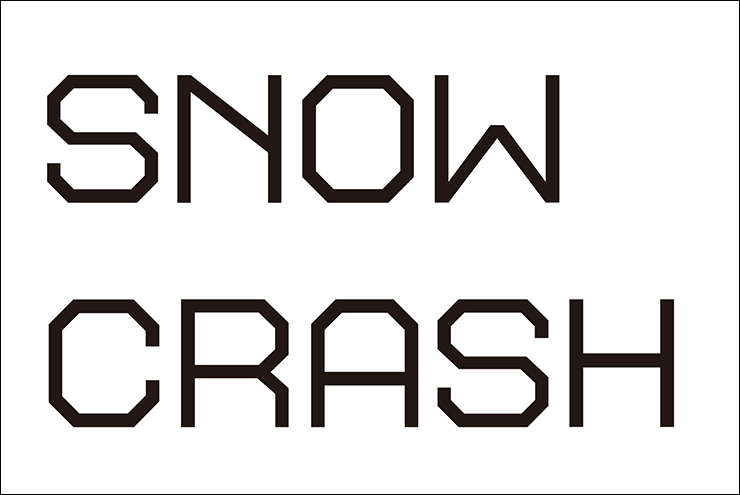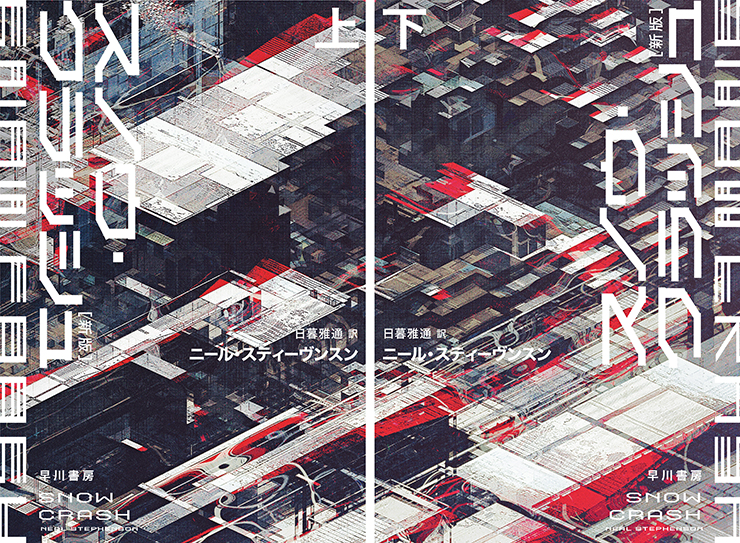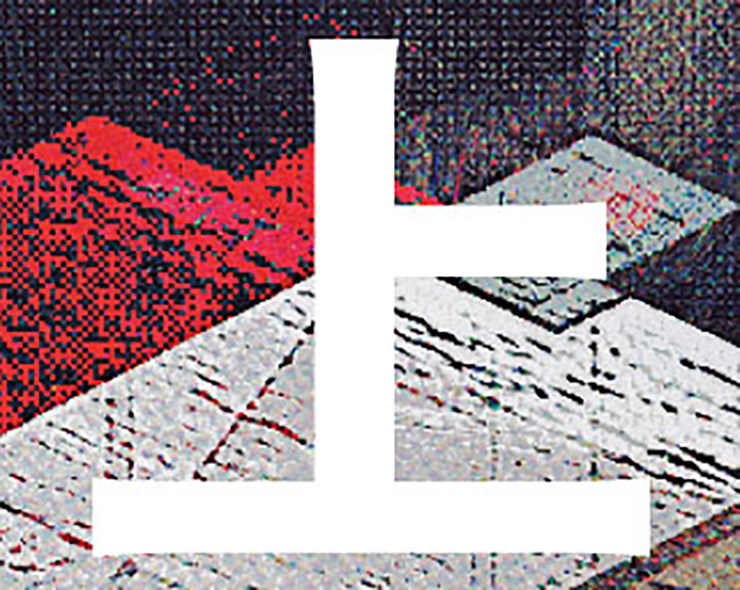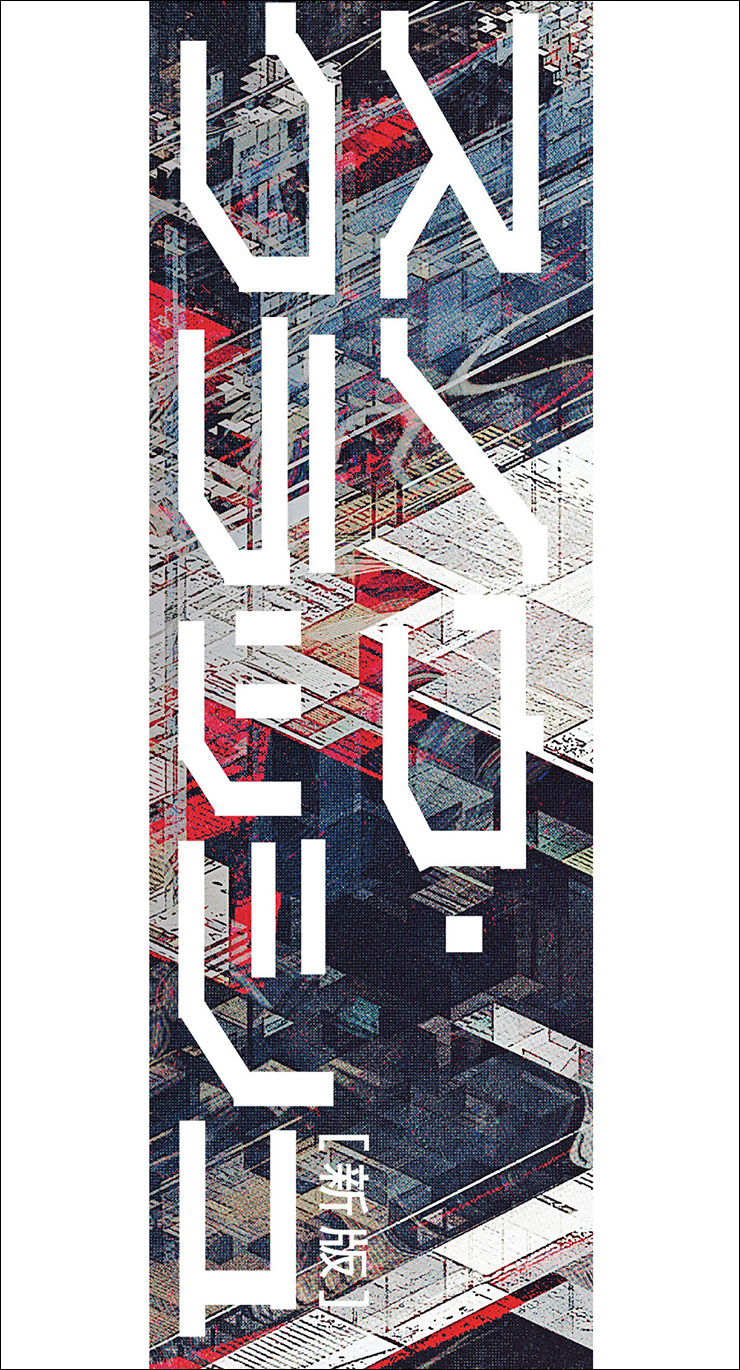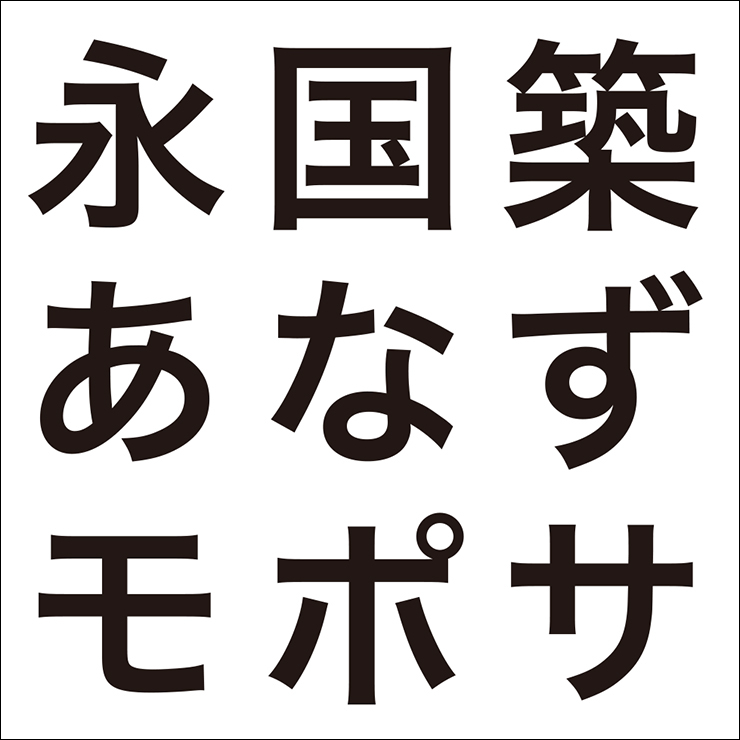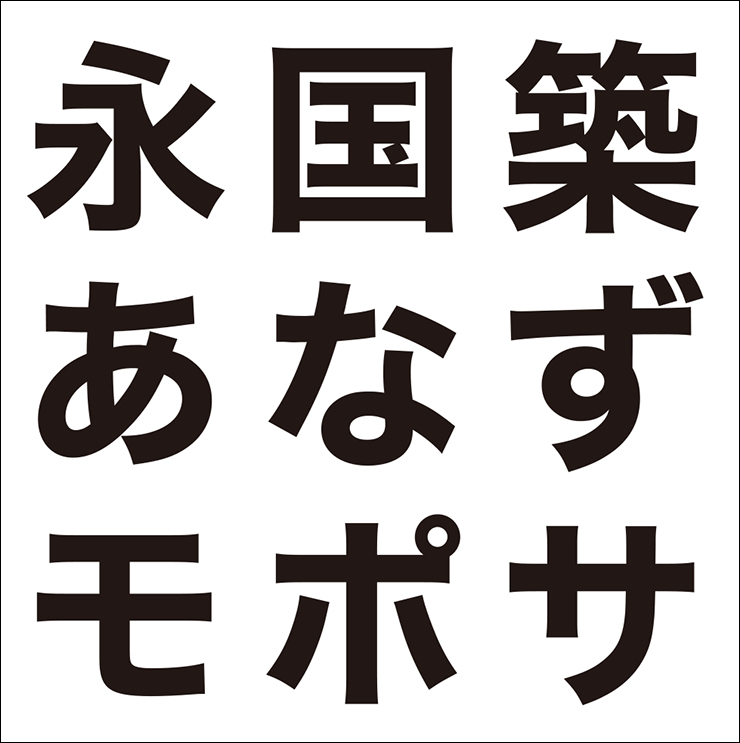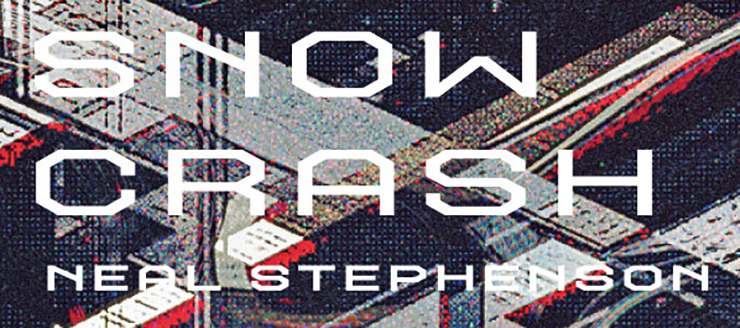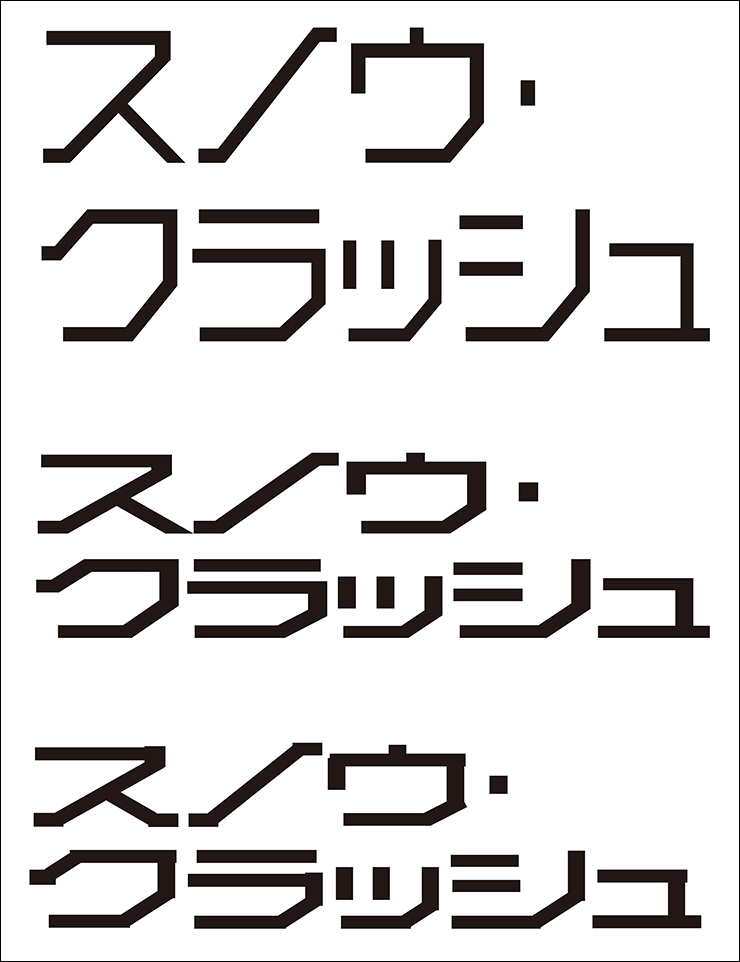
●Designer:早川書房デザイン室
今回はSF小説の金字塔、書籍『スノウ・クラッシュ〔新版〕/ニール・スティーヴンスン(著)、日暮雅通(訳)』(早川書房)で使用されたタイトルフォントを紹介。
直線的かつ規則的な文字で“何か”が伝播していくイメージに
仮想空間およびそのサービスを意味する「メタバース(作中での表記はメタヴァース)」という造語を生み出し、シリコンバレーの起業家たちにも大きな影響を与えたSF小説の金字塔『スノウ・クラッシュ〔新版〕/ニール・スティーヴンスン(著)、日暮雅通(訳)』。仮想空間と現実世界の両方にばら撒かれた謎のウイルス「スノウ・クラッシュ」をめぐる陰謀と、それに巻き込まれていくピザ配達人・ヒロの姿が描かれている。長らく待ち望まれていた復刊に際してカバーデザインもリニューアルされた。
表紙カバーでは、仮想空間やウイルスをモチーフにした作品の世界観が、直線的かつ規則的なタイトルロゴやイラストなどで象徴的に表現されている。デザインを担当した早川書房デザイン室によると「最初はメタバースに寄せたデザインを考えていましたが、編集からのリクエストもあってSFに寄りすぎない方向でデザインすることになりました。タイトルの『スノウ・クラッシュ』はウイルスの名前で、その“何か”が伝播していくようなイメージは『メタバース』にも通じるものがあるかなと考え、そういったイメージで作っています」とのこと。
Font.01「ギガG M」
イラストに合わせて規則的にカクカクしている文字に
メインタイトルの文字は、八角形を基本形状としてデザインされた「ギガG M」(視覚デザイン研究所)がベースに。規則的にカクカクしている印象的なフォルムがイラストにマッチしていたため選択された。
右図は、その加工工程。早川書房デザイン室によれば「平体をかけたりイラストの斜角に合わせて変形したりして微調整しながら、最終的に直線でトレースし直して仕上げています」とのことだ。
Font.02「ヒラギノ角ゴシック W7」
可読性を考慮してオーソドックスなゴシック体を選択
著者名「ニール・スティーヴンスン」部分の文字は、現代的な明るさを持ちながらオーソドックスな印象もあるゴシック体「ヒラギノ角ゴシック W7」(SCREENグラフィックソリューションズ)に。可読性を考慮して、字面がやや大きめで読みやすい角ゴシック体が選択された。
Font.03「ギガG M」
タイトルロゴに合わせて直線的な文字を
タイトルや著者名の欧文部分は、メインタイトルと同じく直線的なフォルムのデザイン書体「ギガG M」(視覚デザイン研究所)がベースに。カクカクしたフォルムがイラストにマッチしていたため選択された。早川書房デザイン室によれば「メインタイトルと同様の印象になるよう、同じ書体をベースに変形して使用しています」とのこと。
Font.04「ヒラギノ角ゴシック W6」
著者名と同じ書体で読みやすくベーシックに
巻数の「上」や「下」の文字は、可読性を考慮して、著者名と同じベーシックな角ゴシック体「ヒラギノ角ゴシック」(SCREENグラフィックソリューションズ)が選択された。著者名部分の文字とのバランスを考慮して、ウェイトはそれより若干細い「W6」が採用されている。